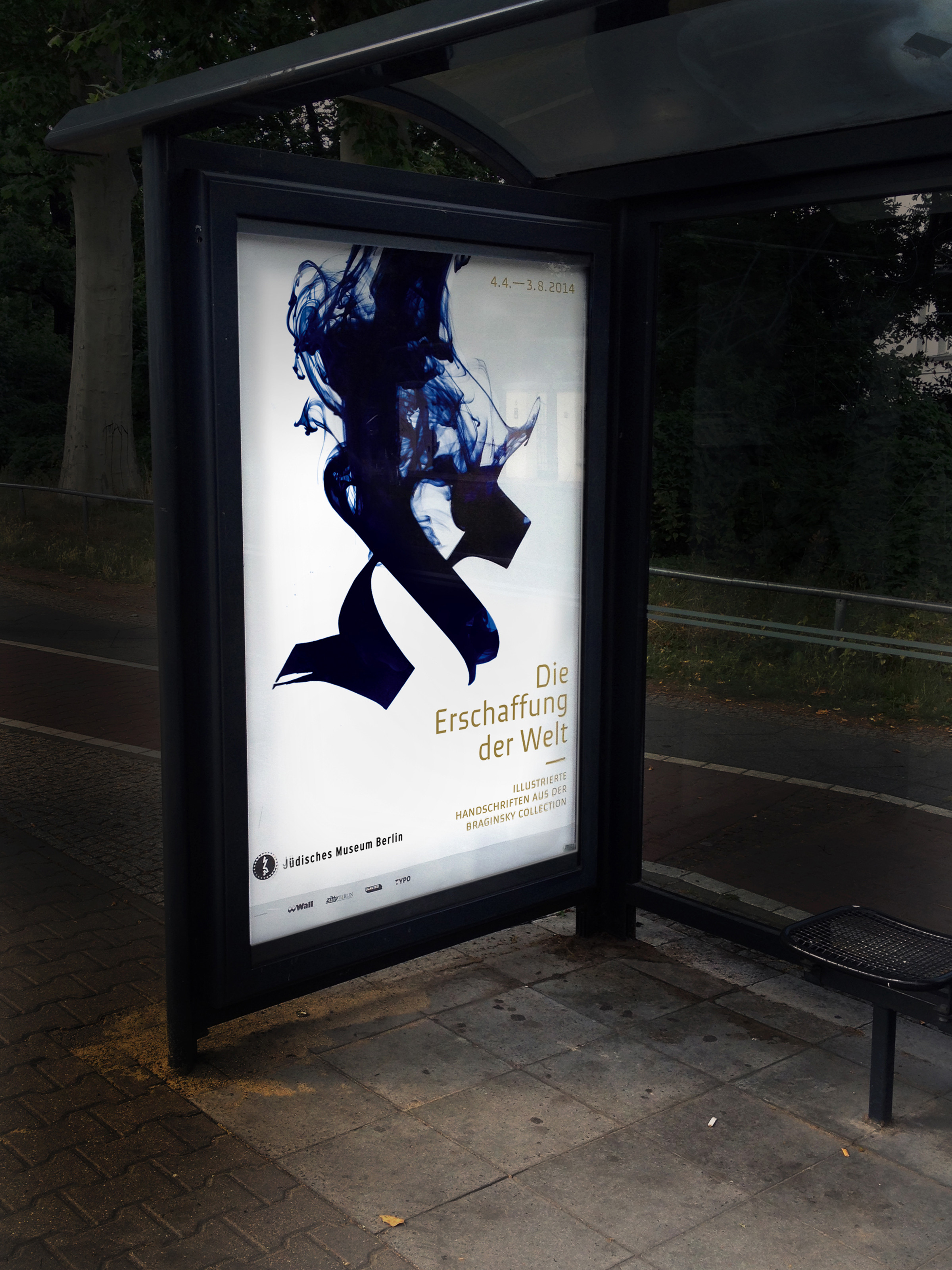
Keyvisual, Plakate, Kommunikationsmittel
Die Braginsky Collection ist eine spektakuläre Sammlung hebräischer Handschriften. Sie umfasst mittelalterliche Schriftstücke, kunstvoll angefertigte Hochzeitsverträge, reich illustrierte Schriftrollen, illuminierte Handschriften und wertvolle Drucke.
Wir entwickelten ein Keyvisual und gestalteten alle Kommunikationsmittel zur Ausstellung von Plakaten in unterschiedlichen Ausführungen, Fassadenbanner, bis hin zu den Eintrittskarten. Die Tusche entwickelt sich zum kalligrafierten Buchstaben »Alef«, der den ersten Buchstaben im hebräischen Alphabet darstellt. Er zeigt Entwicklung, Entstehung und Bewegung – sowie auf eine sehr ästhetische Art – die Schönheit und den Ursprung der hebräischen Schriftkultur. Auch im Bezug auf den Ausstellungstitel »Die Erschaffung der Welt« hat dieser Ansatz überzeugt.